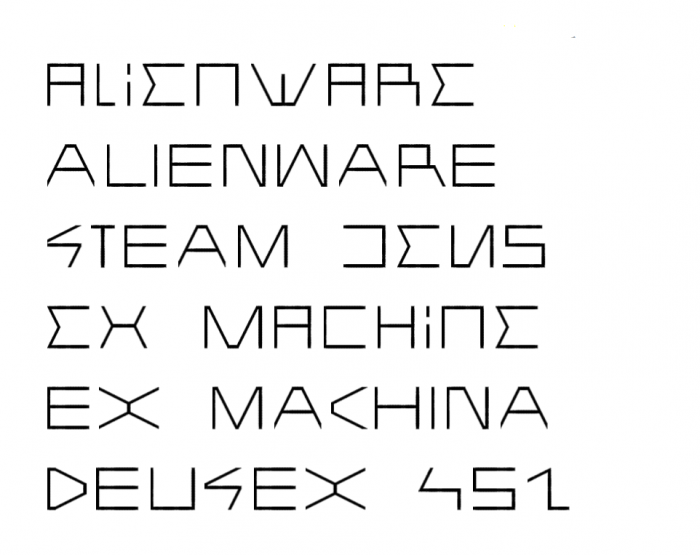
• Такой агрессивный футуристический стиль стал считаться геймерским. И теперь представьте, что он ещё и светится!
Such an aggressive futuristic style has become considered gaming style. And now imagine that it also glows!
Perhaps this is the limit of my capabilities.